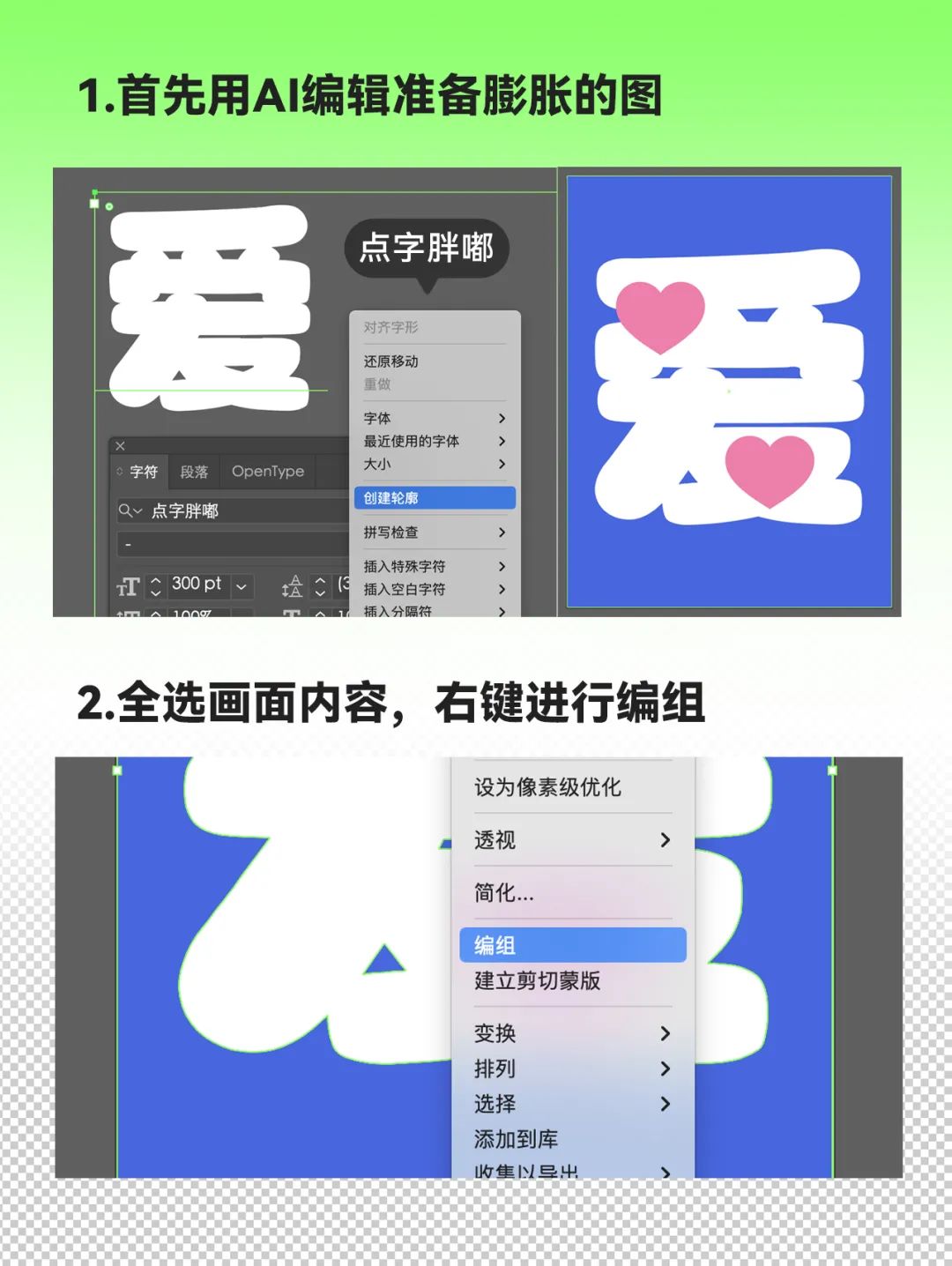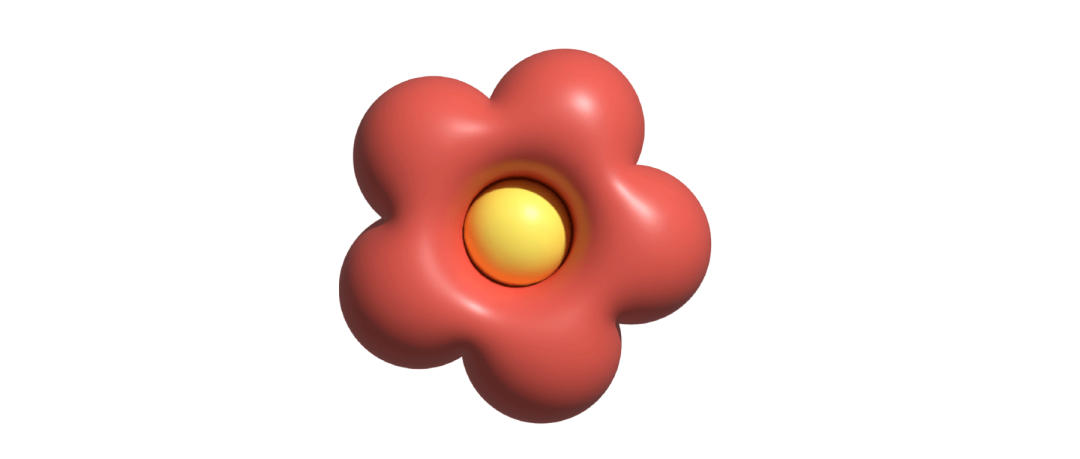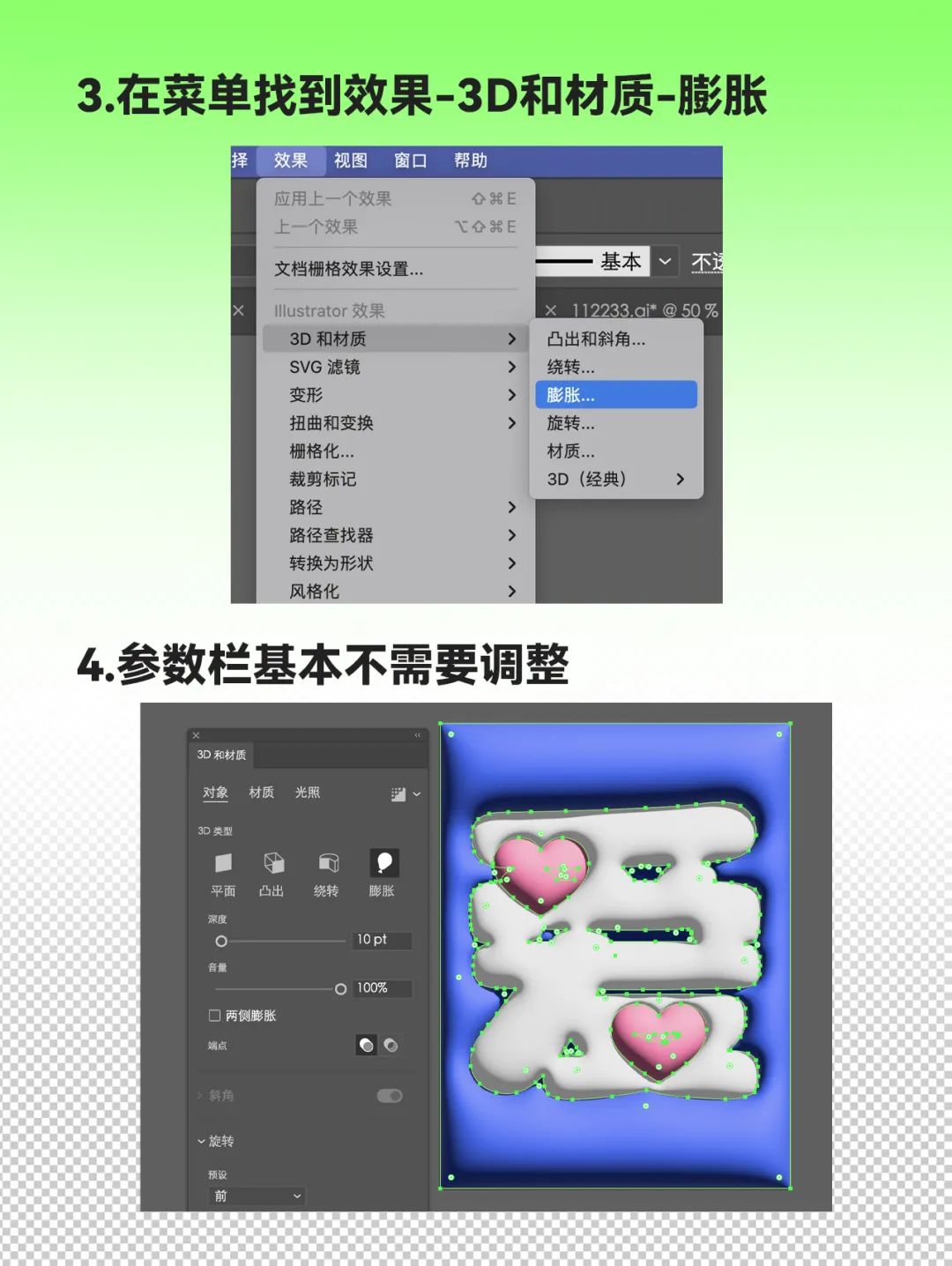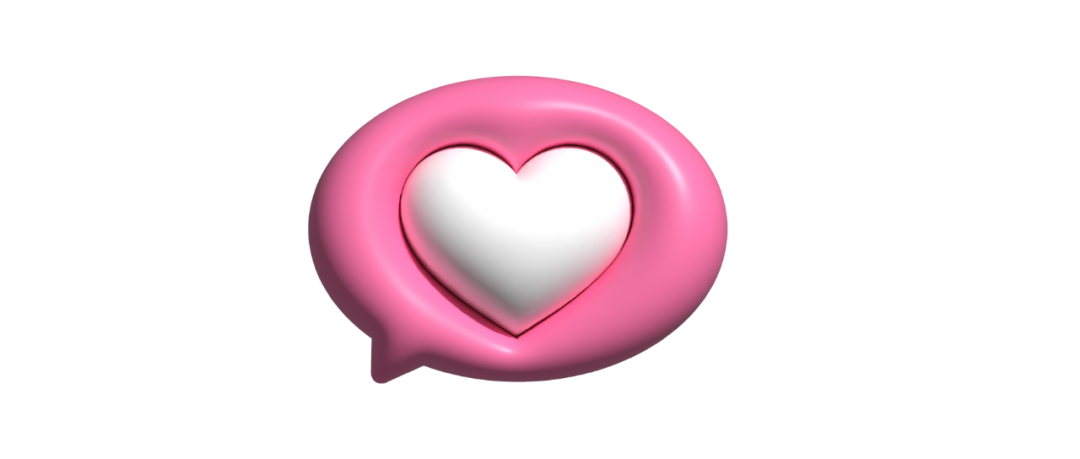
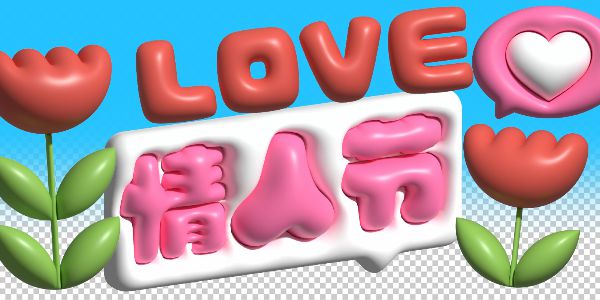
这招一键膨胀的AI教程,还拿不下你?
明天就是情人节了,不管有情人没情人,设计狗都要做“最虐狗” 的情人节海报。
所以,柚子速速给你安排一个超简单,最近也超火的膨胀教程~
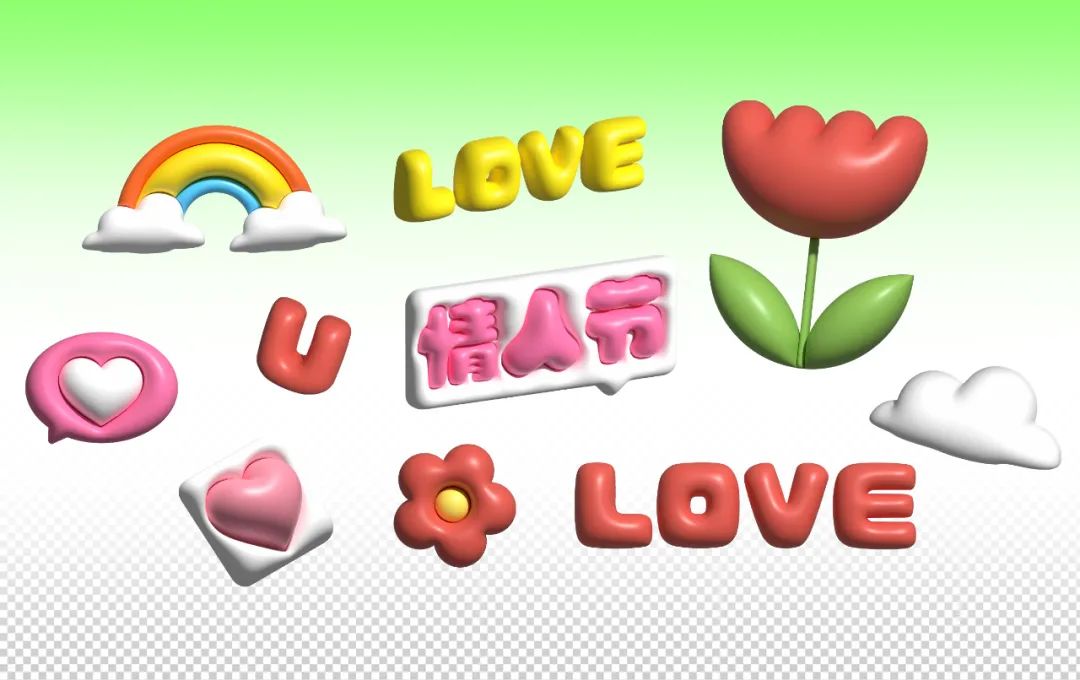
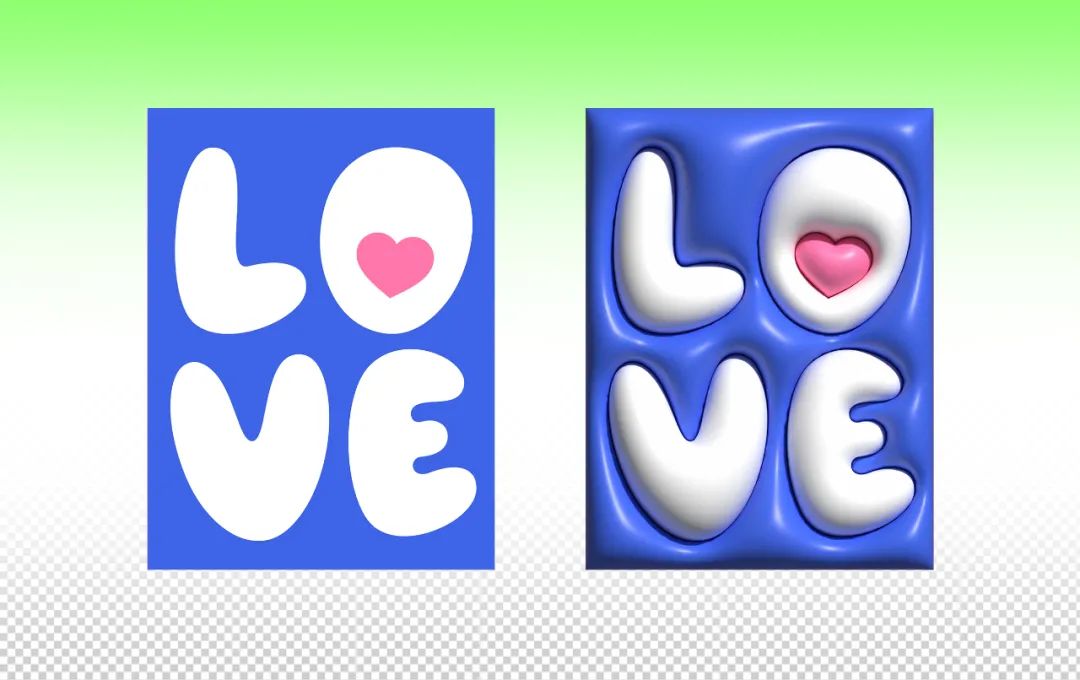
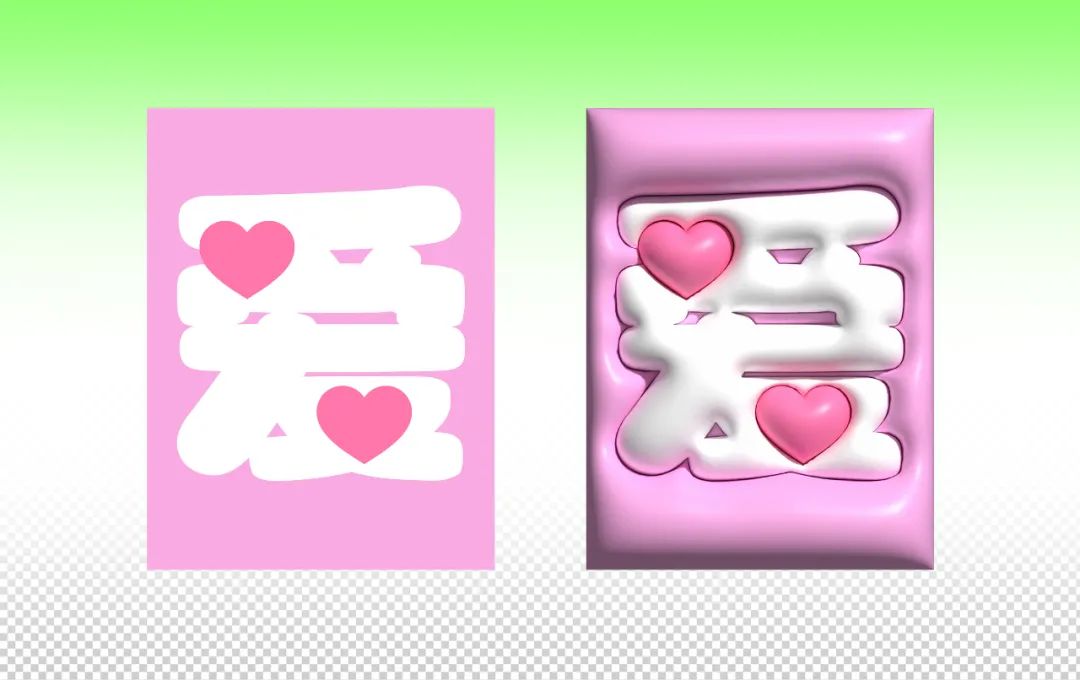
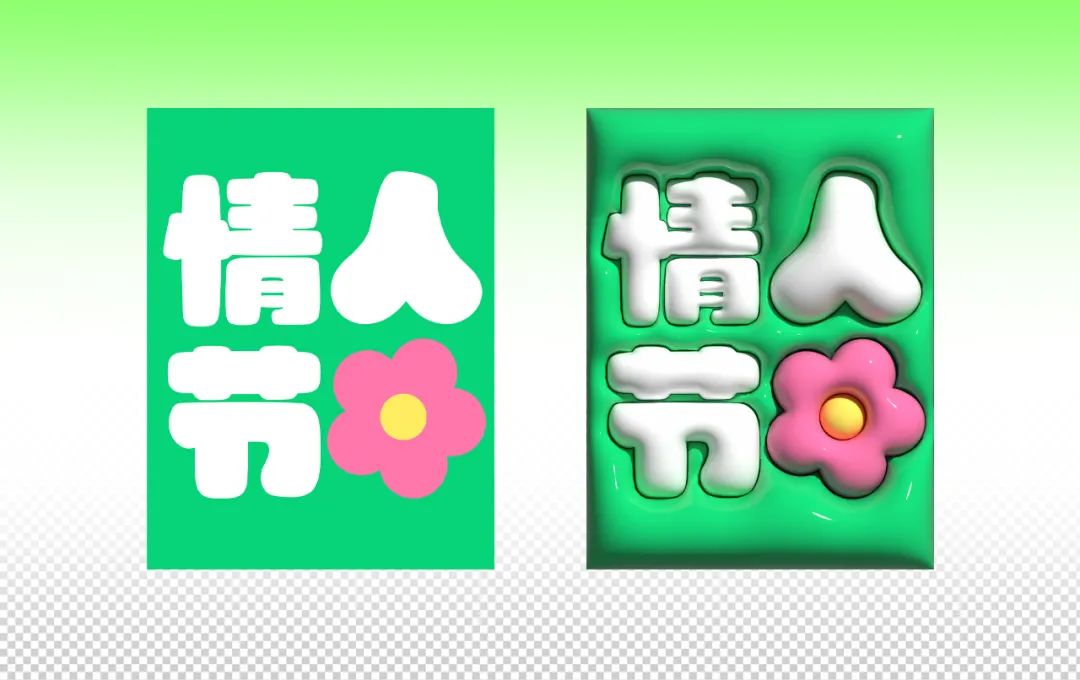
简单快速一键出图,不光做海报还能做图标!有了它🌈宝再也不用担心,老板下班不让我走了😄
Duangduang的图,就要配Duangduang的字体,最近新上的点字胖嘟就最合适不过了😊快去字由客户端用起来~